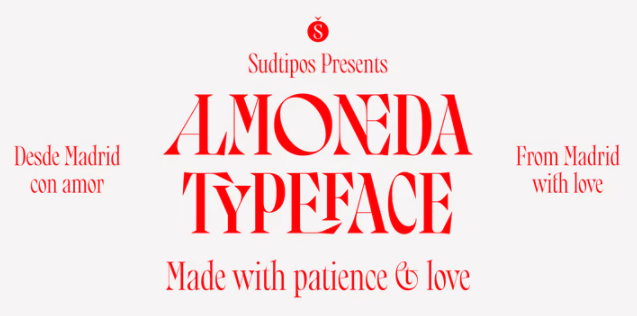
Альмонеда: Продажа на публичных торгах движимого имущества, как правило, бывшего в употреблении. А также: частная и добровольная продажа драгоценностей и барахла, совершаемая без вмешательства правосудия. Раньше это было не что иное, как рынок или продажа вещей и трофеев, завоеванных у врага на войне.
Сегодня альмонеда практически ассоциируется с местами, где продаются "старые вещи", а в Мадриде они обычно сосредоточены в районе Эль-Растро, рынка под открытым небом, который устраивается по воскресеньям и некоторым праздникам в центре Мадрида. Там можно найти все, что угодно, а если долго ходить и внимательно смотреть, то и отличные типографские находки. Именно там я нахожу большое количество элементов (обычно конца девятнадцатого и начала двадцатого века), таких как коробки, плакаты, книги и т.д., в которых появляются прописные буквы разнообразных форм, буквы, вписанные в шрифт, редкие лигатуры... Кроме того, многие элементы, извлеченные из уличных вывесок, плитки из баров и памятных элементов Мадрида, были использованы для завершения этого дизайна шрифта, выполненного с заботой и терпением.
Так родился Almoneda, современный шрифт с выраженной осью и большим контрастом, а также прописной буквы с несколькими наборами символов, с которыми можно играть и наслаждаться. Он также включает в себя большое количество лигатур и произвольных лигатур. Шрифт Variable включен в лицензию полного пакета.
Альмонеда: Продажа на публичных торгах движимого имущества, как правило, бывшего в употреблении. А также: частная и добровольная продажа драгоценностей и барахла, совершаемая без вмешательства правосудия. Раньше это было не что иное, как рынок или продажа вещей и трофеев, завоеванных у врага на войне.
Сегодня альмонеда практически ассоциируется с местами, где продаются "старые вещи", а в Мадриде они обычно сосредоточены в районе Эль-Растро, рынка под открытым небом, который устраивается по воскресеньям и некоторым праздникам в центре Мадрида. Там можно найти все, что угодно, а если долго ходить и внимательно смотреть, то и отличные типографские находки. Именно там я нахожу большое количество элементов (обычно конца девятнадцатого и начала двадцатого века), таких как коробки, плакаты, книги и т.д., в которых появляются прописные буквы разнообразных форм, буквы, вписанные в шрифт, редкие лигатуры... Кроме того, многие элементы, извлеченные из уличных вывесок, плитки из баров и памятных элементов Мадрида, были использованы для завершения этого дизайна шрифта, выполненного с заботой и терпением.
Так родился Almoneda, современный шрифт с выраженной осью и большим контрастом, а также прописной буквы с несколькими наборами символов, с которыми можно играть и наслаждаться. Он также включает в себя большое количество лигатур и произвольных лигатур. Шрифт Variable включен в лицензию полного пакета.